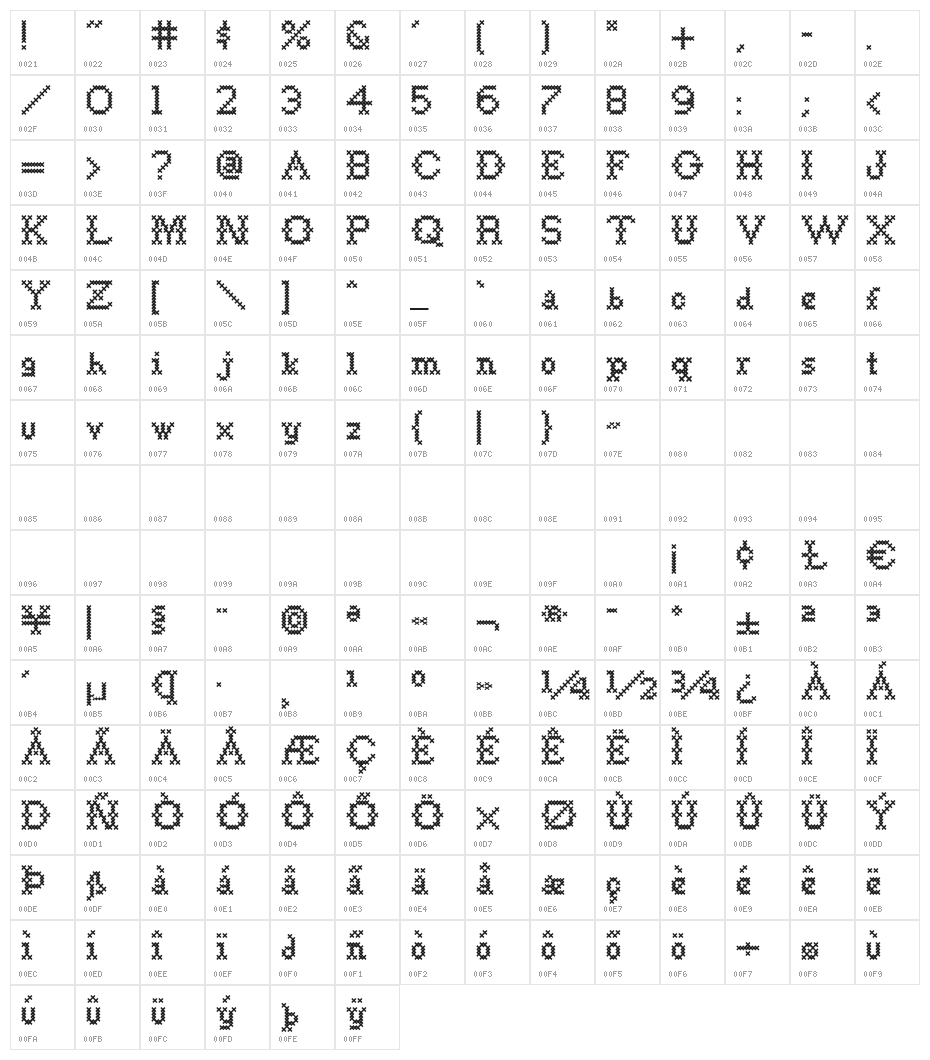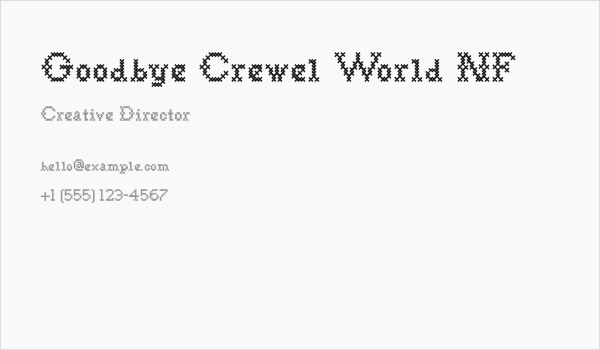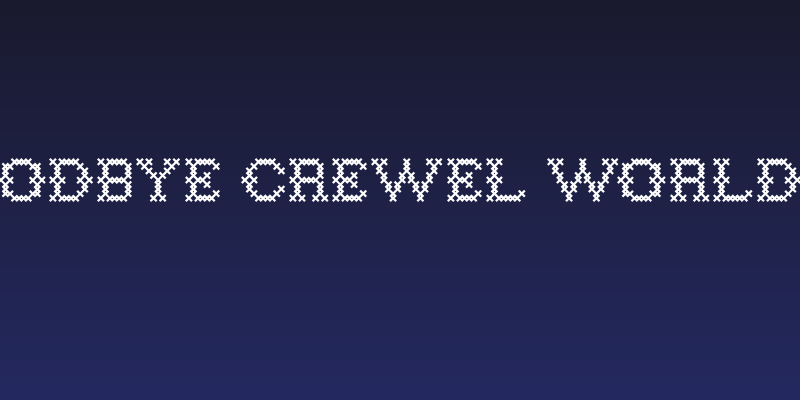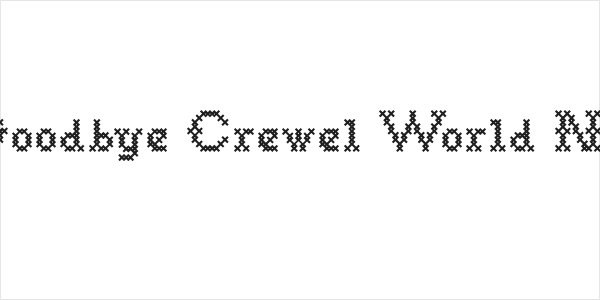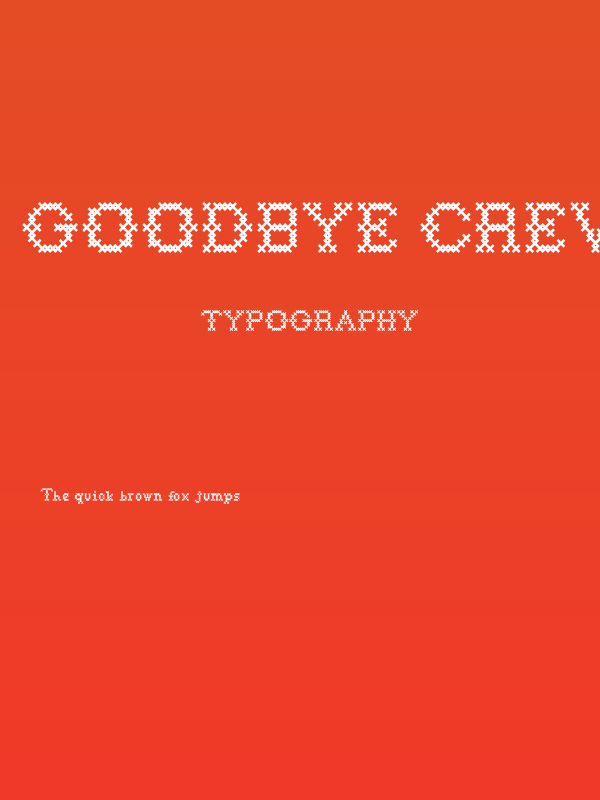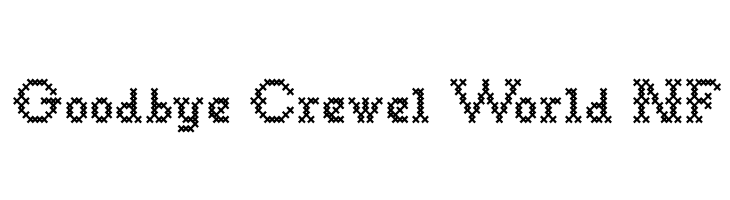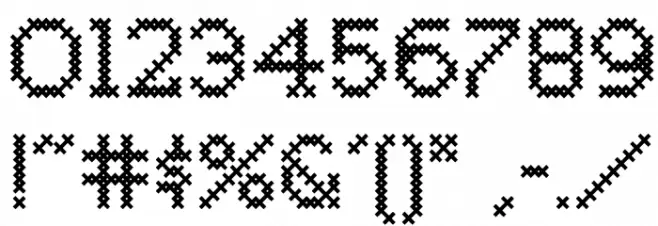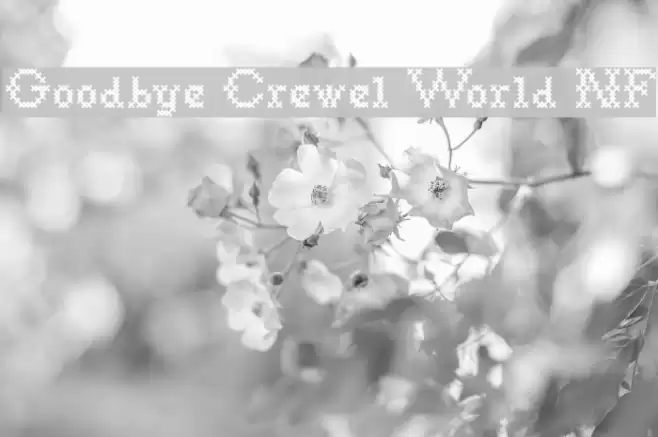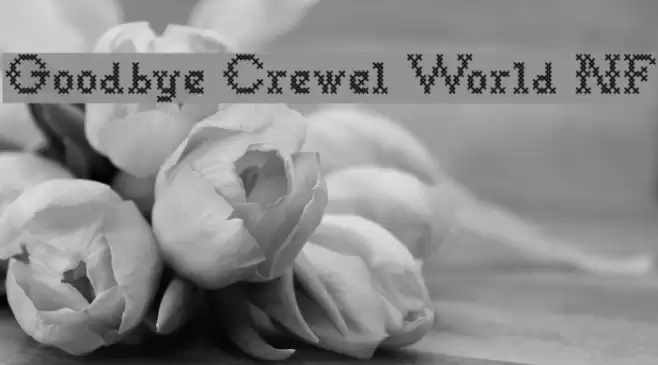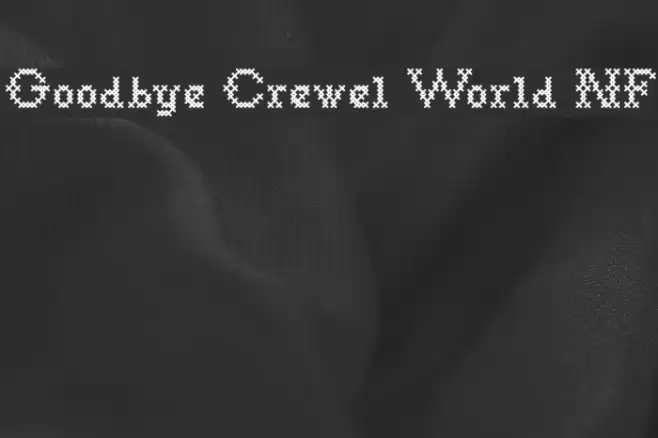
Goodbye Crewel World NF Font
| حالة الاستخدام | Headlines, Logos, Decorative text |
| مشاريع مقترحة | Ideal for craft-themed projects, DIY blogs, greeting cards, and any design needing a handmade touch. |